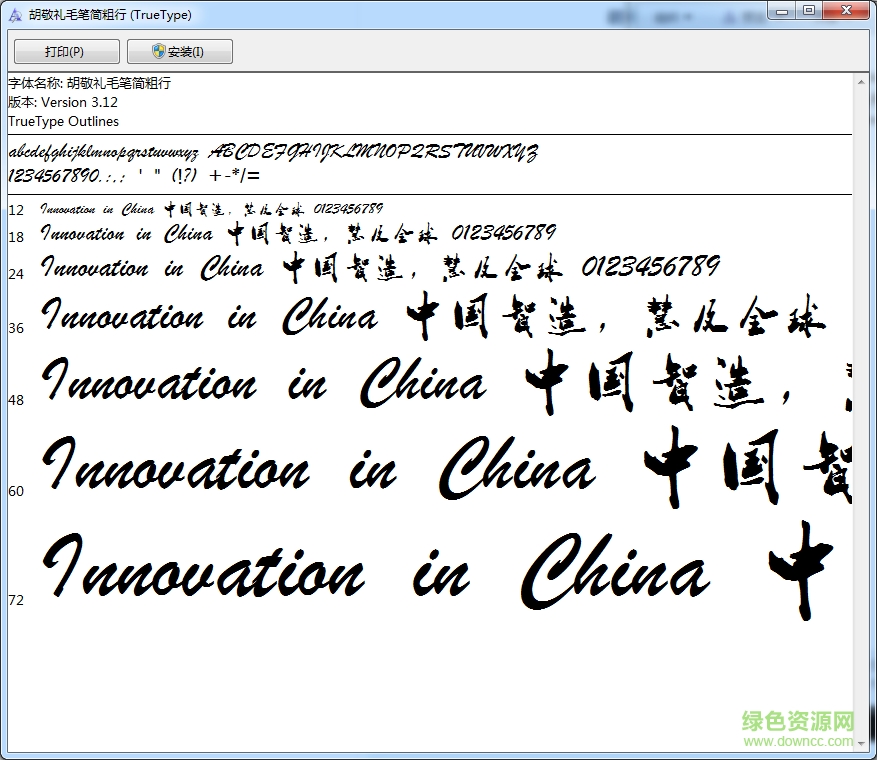
胡敬禮毛筆粗行字體
胡敬禮毛筆粗行字體是一款比較常用的電腦字體,字體粗細有致,線條感十足極具美感,適用于海報設(shè)計、圖文印刷、美工創(chuàng)作等多種領(lǐng)域,一鍵安裝便可使用??靵砭G色資源網(wǎng)下載體驗吧!
胡敬禮毛筆粗行字體介紹
胡敬禮毛筆粗行字體是一款用于毛筆手寫設(shè)計方面的字體,整體字體筆畫運筆飄忽快捷,筆跡粗壯,是一種風(fēng)格相當獨特的字體。該字體適用于創(chuàng)意設(shè)計、藝術(shù)設(shè)計、書寫設(shè)計等方面,需要的話可以來下載使用。